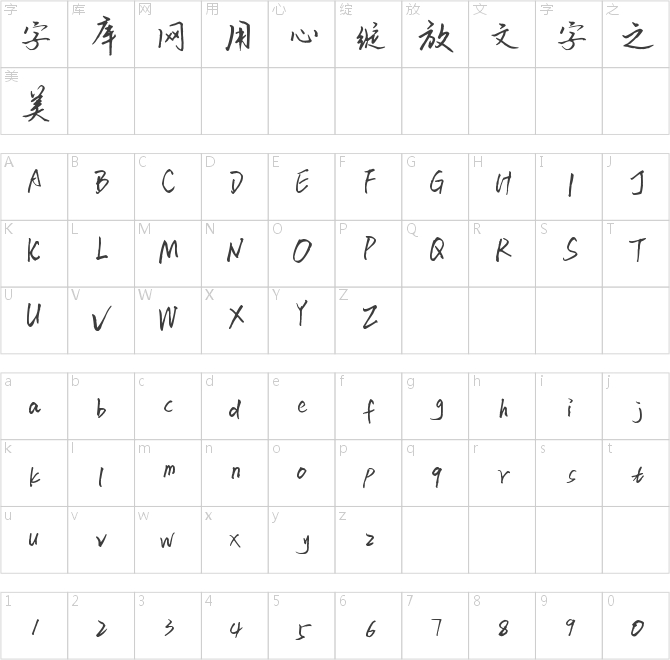
字體名稱: 字在如風(fēng)
字在如風(fēng)
字在如風(fēng)介紹
字在如風(fēng)字體字庫是一款讓人賞心悅目、百看不厭的中文字體,適合各類廣告和產(chǎn)品包裝設(shè)計(jì)應(yīng)用,字體大小3.49MB,格式為TTF字體,上傳用戶是伍佰,作者/版權(quán)方為未知